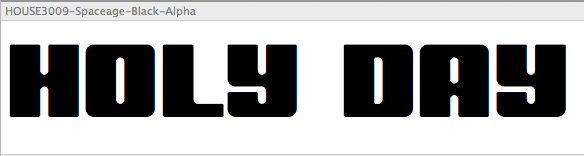
Suche flächige Schrift
... Suche flächige Schrift, deren Negativ-Form in Einzelbuchstaben sowie im Wort-Verbund als Foto-Motiv-Maske geeignet ist.
Die Anmutug "Holyday / Freizeit / Wasser / Surfen" muß nicht sein. Hauptsache, die Schrift bietet viel Fläche für eine Bild-Füllung.
Hat jemand eine Idee?
Die Spaceage Black von House ist brutal fett:
als Foto-Motiv-Maske geeignet ist.
zu fett, wie klimax oder akimoto ist dann glaube ich weniger hilfreich, sondern eher noch lesbare fette buchstaben. ich hab das mal mit einer engesetzten compacta in versalsatz gemacht, sah eigentlich sehr gut aus und der text war auch noch gut lesbar.
kommt evtl. aber auf die menge des textes an. bei weniger text könnte man auch die klimax, akimoto oder facebuster verwenden.
uiii, die würden mich ja auch mal interessieren.
die 'graphit'?
offiziell: anfang nächstes frühjahr - fehlen noch etliche sonderzeichen und die ein oder andere ligatur für absoluten genuss des schwarzwertes.
praktisch: ab jetzt. ich freu' mich wenn jemand die schrift testet.
die 'say it fat'?